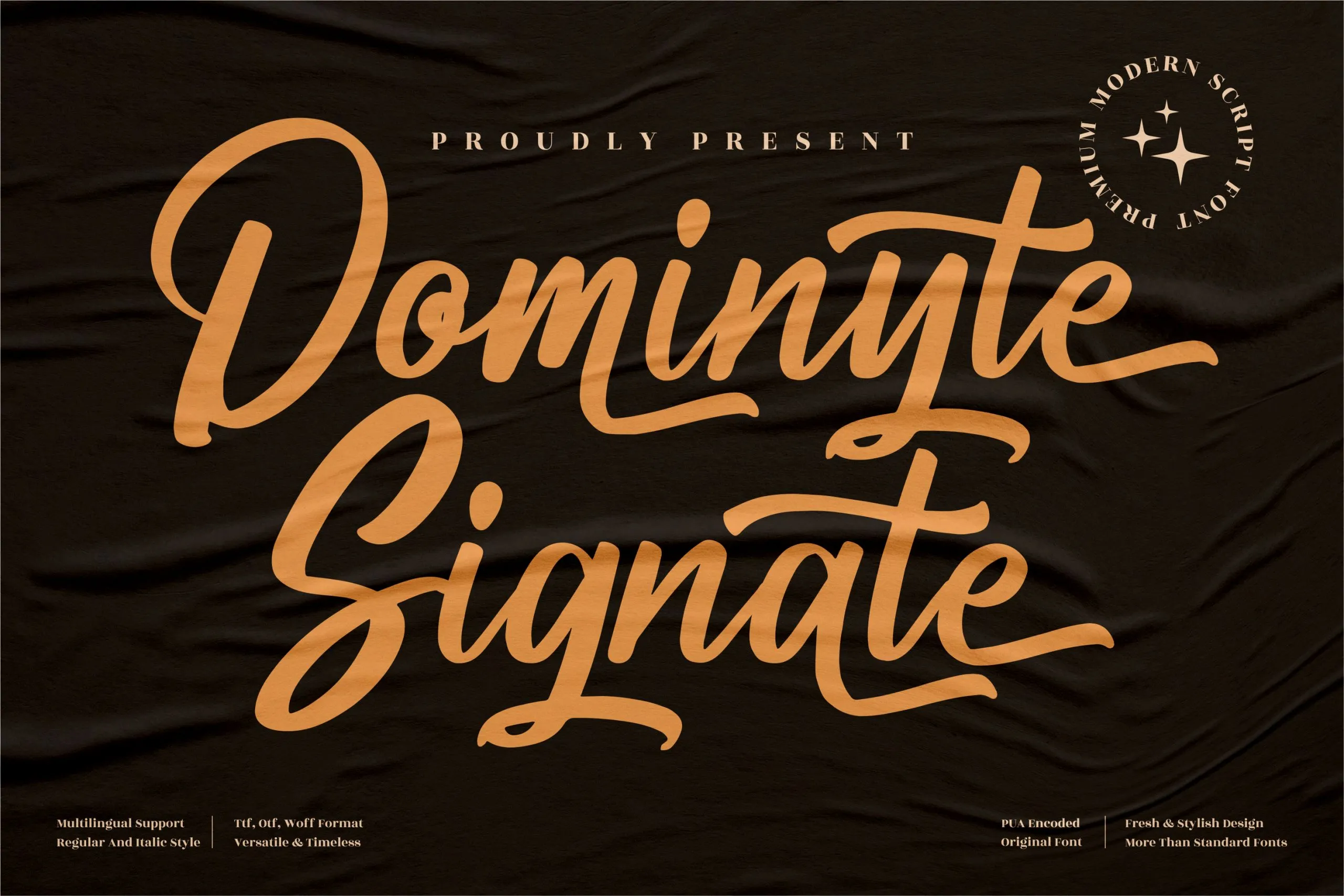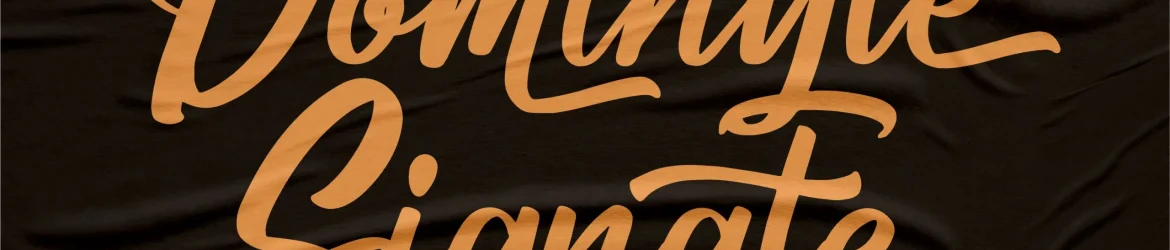
A fonte ‘Dominyte Signate Font’ é perfeita para qualquer projeto que precise de uma assinatura única e sofisticada. Feita pelo designer perspectype, esta fonte premium é ideal para aplicar em logos, projetos de marca, designs de móveis de casa, embalagens de produtos, mugs personalizados, cartões de citação, convites de festa, capas de livros e mais. Sua aparência elegante e sofisticada se encaixa perfeitamente em quase todos os tipos de projetos que exijam um toque de luxo e autenticidade. Seja para criar sua própria marca com estilo ou personalizar produtos finos, a ‘Dominyte Signate Font’ é uma escolha ótima para deixar seu trabalho mais elegante e profissional.